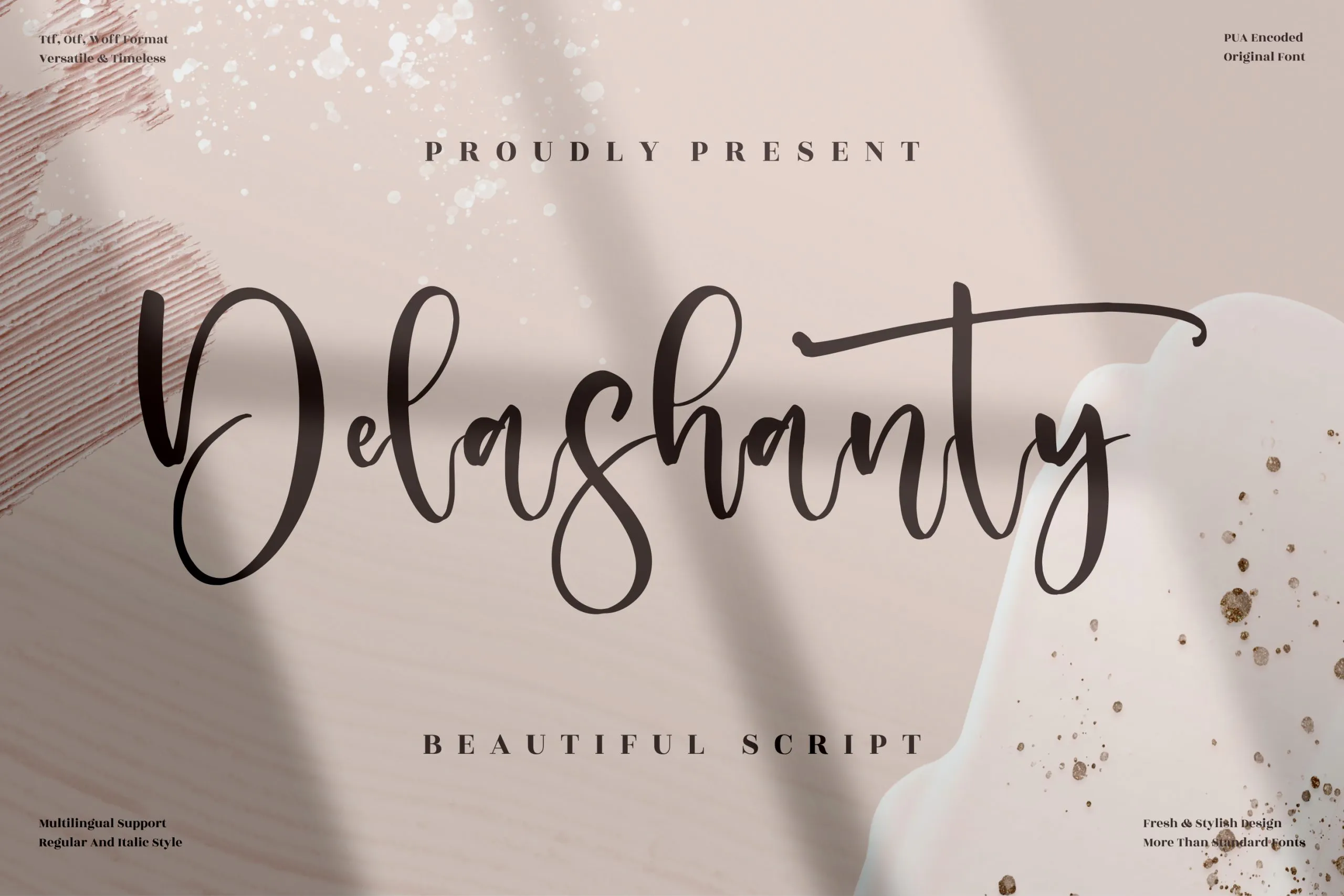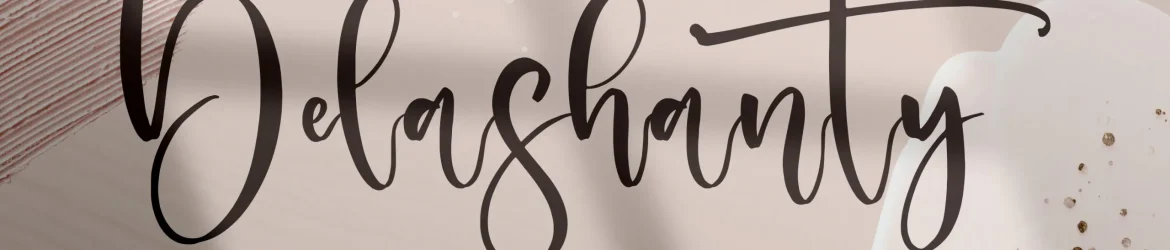
Delashanty Font – Download Grátis
A fonte “Delashanty Font” é uma elegante seleção para quem busca adicionar um toque romântico aos seus projetos digitais e impressos. Seja para criar logomarcas, embalagens de produtos ou até mesmo cartões de visita personalizados, essa fonte de escrita proporcionará um brilho atraente e único. Ideal para uma variedade de aplicações, incluindo designs em homewares, embalagem de produtos, materiais decorativos e até mesmo criação de fotografias ou marcadores. A “Delashanty Font” é perfeita para aqueles momentos especiais como presentes personalizados, festivais temáticos e qualquer outra ocasião que você desejar celebrar com uma escrita delicada e romântica. Essa fonte de chamamento do designer perspectype oferece um toque especial a qualquer projeto, tornando-a um recurso indispensável para designers gráficos e amadores.